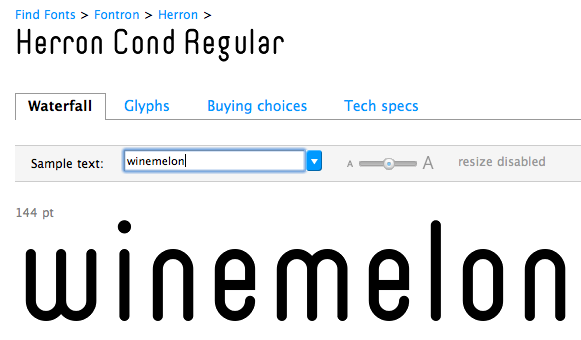
Suche diese, oder ähnliche Schrift!
suche diese, oder eine vergleichbare Schriftart.
Mir geht es dabei vor allem um die Rundungen bei den Buchstaben. Es muss also nicht unbedingt in die Condensed-Richtung wie bei dem Beispiel gehen.
Die Herron Cond Regular, falls eine Rounded auch geht.
Schriftmuster ist leider nicht möglich, keine Ahnung warum, also dann per Screenshot: